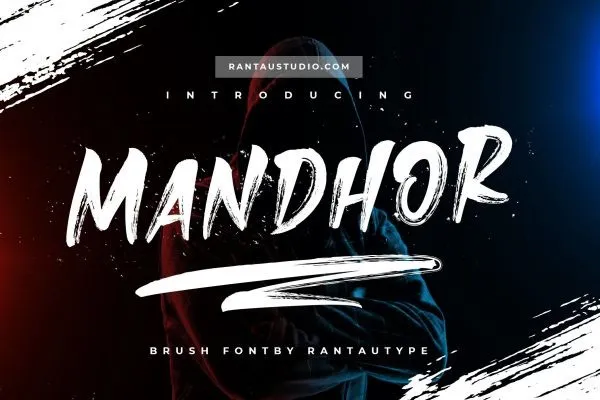
A Mandhor é uma fonte script bold projetada para logotipos que oferece uma experiência única tanto no uso quanto na visualização. Esta seleção de letras tem um toque moderno e elegante, característica essa que se estende a sua leitura fácil e ao mesmo tempo poderosa e divertida. Além disso, ela vem acompanhada de Swash para aqueles projetos onde uma adição extra pode ser benéfica. Esta font é perfeita para uso em projetos como fotos com marca d’água, logos, frases curtas para capas de livros, design de revistas e camisetas. Além disso, a Mandhor é também uma escolha ideal para aplicar em vários outros tipos de projetos. Seja na criação de um selo ou em desenhos que exigem estilo forte, essa font oferece os elementos certos para manter seu design atraente e único. Ela é tanto moderna quanto divertida, o que torna-a uma opção popular entre designers que buscam um toque inovador sem sacrificar a legibilidade da letra. Combinando elegância com força, a Mandhor está repleta de qualidades que a tornam uma escolha inteligente para diversos projetos de design. Sua simplicidade e robustez permitem que seja usada em qualquer projeto onde o estilo é essencial.